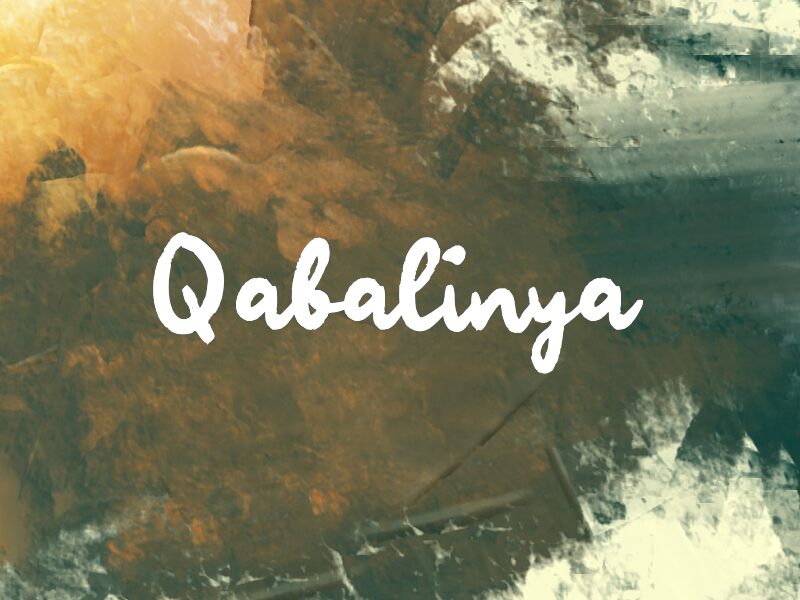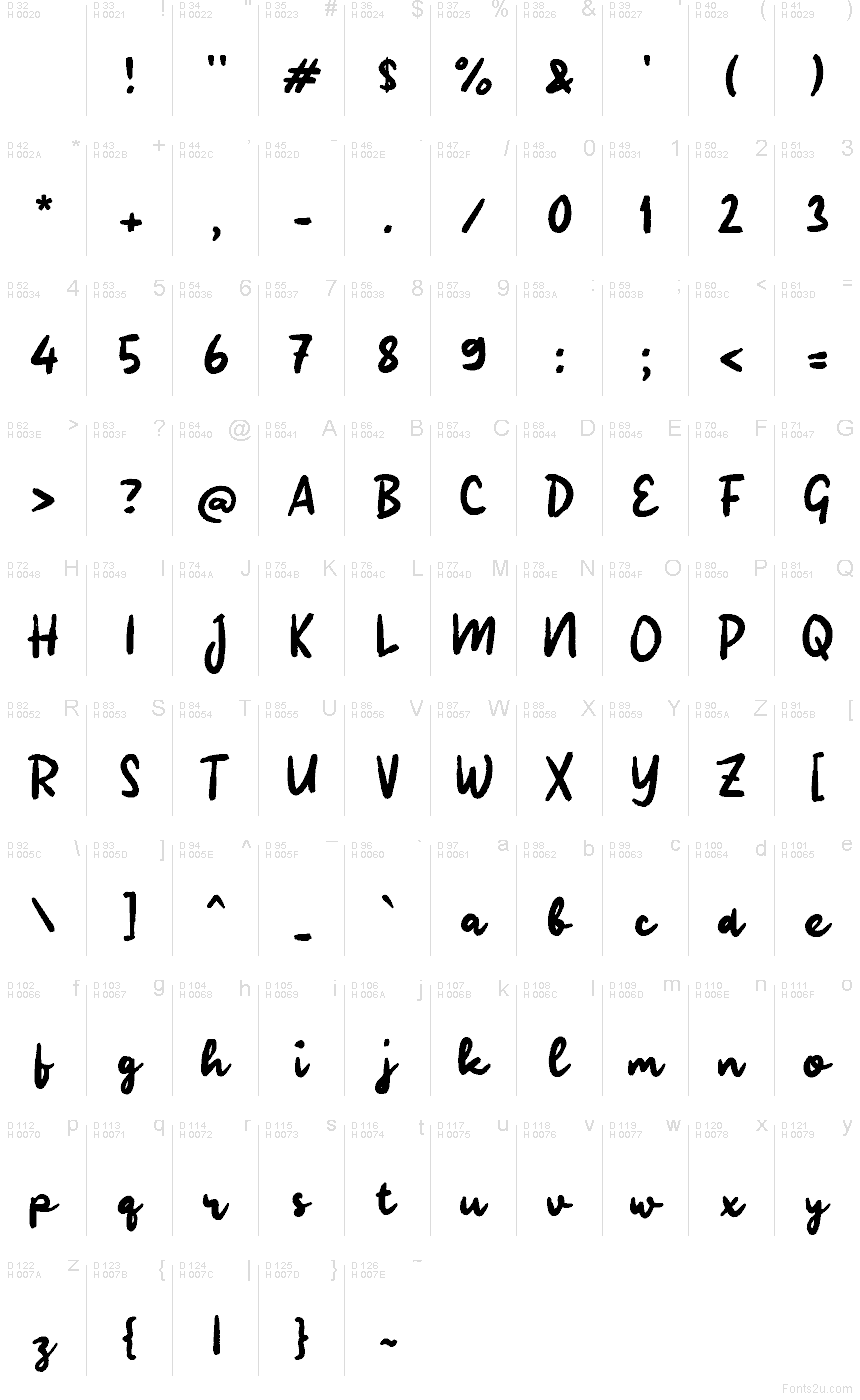
Qabalinya
Qabalinya di Wep è un font script a pennello gratuito, caratterizzato da un movimento calligrafico rilassato e un tocco rétro che ricorda le insegne dipinte a mano. Le lettere si muovono con un ritmo naturale, fatte di tratti arrotondati, raccordi morbidi e ascendenti alte e ricciolute che rendono il font informale e mai troppo artefatto.
Si adatta perfettamente a branding, menù di caffetterie, packaging, titoli di locandine, card per citazioni sui social e copertine che richiedono un tocco umano. Essendo un font gratuito, è ottimo anche per titoli, bozze di loghi e nomi su inviti, perché la consistenza del pennello largo e le connessioni vivaci danno anche alle frasi più brevi un aspetto vissuto, come scritto a mano.